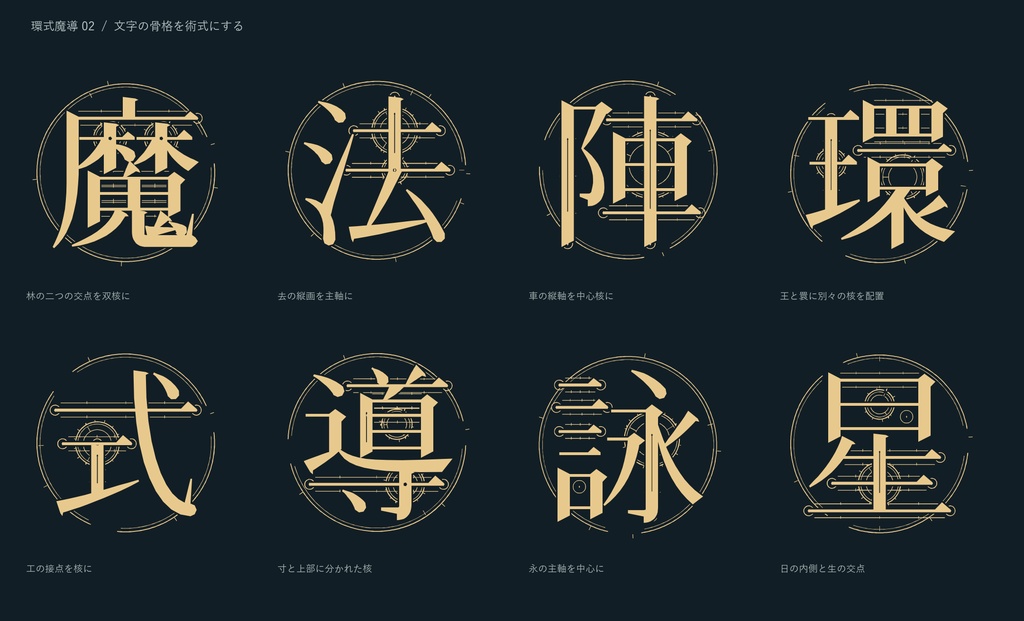
環式魔導|魔法陣構造の日本語ディスプレイフォント
文字そのものを魔法陣にする、日本語ディスプレイフォントです。 文字の画数・長い画・交点・空白を解析し、文字ごとに核、導管、刻印、外周環を組み立てています。外周環の回転、欠け、目盛周期も文字ごとに変わるため、同じ魔法陣を並べた背景には見えません。 ■ 収録 ・常用漢字2,136字を含む日本語文字セット ・かな、英数字、主要記号 ・TrueType(TTF)1書体 ■ 使用例 同人誌の表紙、ゲームの章題、TRPG素材、映像タイトル、配信画面、ロゴ、幻想系の創作物に。 ■ 利用 個人・商用利用可。ロゴ、動画、ゲーム、印刷、配信、同人・商業作品に使用できます。クレジット不要です。 フォントファイル自体の再配布・共有・転売・アップロードは禁止します。ゲームやアプリへの組み込みは、フォントデータを抽出できない形で行ってください。 ※魔法陣の装飾を含む見出し向け書体です。小サイズ本文、長文組版、縦組み、全アプリでの互換性は保証しません。 GlyphWiki KAGEデータを基底に加工・再設計しています。原ライセンスをZIPに同梱しています。